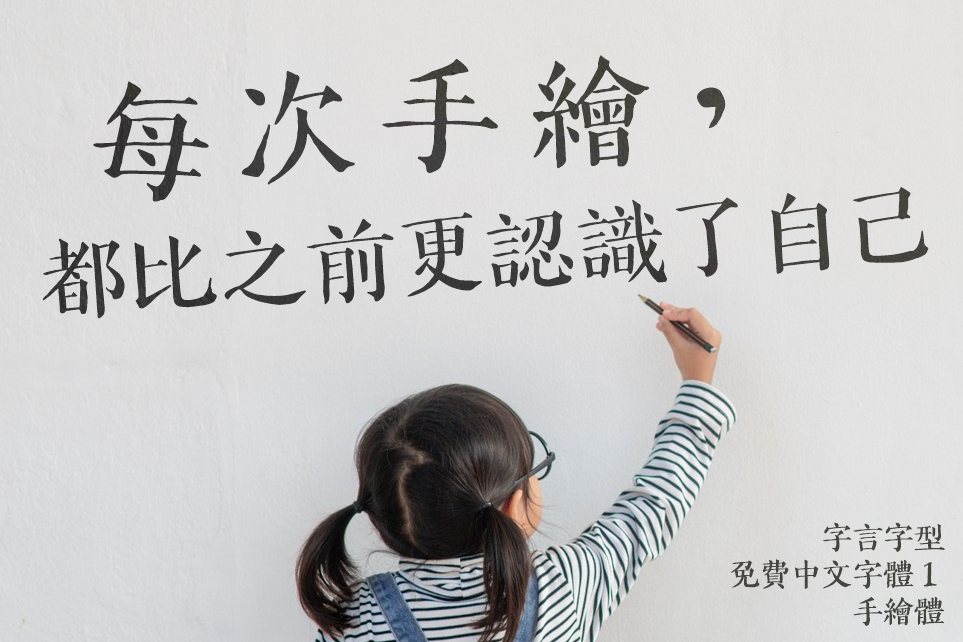
字言字型免費中文字體1—手繪體
閱讀文章之前先為文中名詞做出定義:
字體:文字的風格、造型。如:宋體、黑體。
字形:文字的寫法。如:“玄”的第一筆是點還是豎點,幺是ㄥㄙ形還是ㄑㄙ形。
我們開發了一款要送給各位朋友的全新字型《字言字型免費中文字體1—手繪體》。這款字型採用了手繪塗鴉風格,並以宋體的筆形配上楷體的骨架製成,營造出不同於其他單一風格的造型。融合相同風格的手繪西文,包括精心設計的字距微調(Kerning)及等寬的數字等。
另外,這款字體更收錄了大量的、不同於現代正體字的字形。得益於繁體字形源遠流長,這些字形我們至今都可以輕鬆地在其他印刷字體中看到。這些字形採樣自美術字、書法字、鉛字字形,照相排版機字形等。
·為何採用這些字形?
我們希望除了能在文字造型上展現特色外,字形也是一可以發揮的地方。不僅是由官方機構頒佈的字形,放眼望去,琳琅滿目的字體以及不同的字形,這不正是多元化的象徵嗎?我們收錄的這些字形部件,都是能夠在不同的地方見到,沒有一種部件是我們原創出來的。
這款字體,我們選擇的字形都是不會過度影響文字辨識的字形。我們的選擇主軸如下:
①極為常見的構形不同的字。比如:啟/啓,我們選擇了啓;籲/𥸤,我們選擇了𥸤。
②僅需改動部件,相同部件採取一致的造型。舉例:我們採樣到“鬲”裏面為交叉的融,我們一致修改了隔、獻等字。
③選擇現今更通行的字。比如我們也有搜集到“隂”,但是與今字形相去甚遠,故棄之。
④字型製作者偏愛的字形。像是:出頭兂(潛)、橫撇的戶(戸)等。
我們將這些字形放置在日常情況下能夠輕鬆輸入的事實編碼上(Big5) ,來服務更多的認同我們的設計思路的朋友。此外,此字型的造型也與字形的選擇相映成趣,歡迎免費下載體驗!
字言字型免費中文字體1—手繪體
支援:繁體中文、臺灣台語白話字、羅馬字拼音方案(POJ, TL)、臺灣原民語羅馬字、臺灣客家語拼音方案、漢語拼音(Hànyǔ pīnyīn)